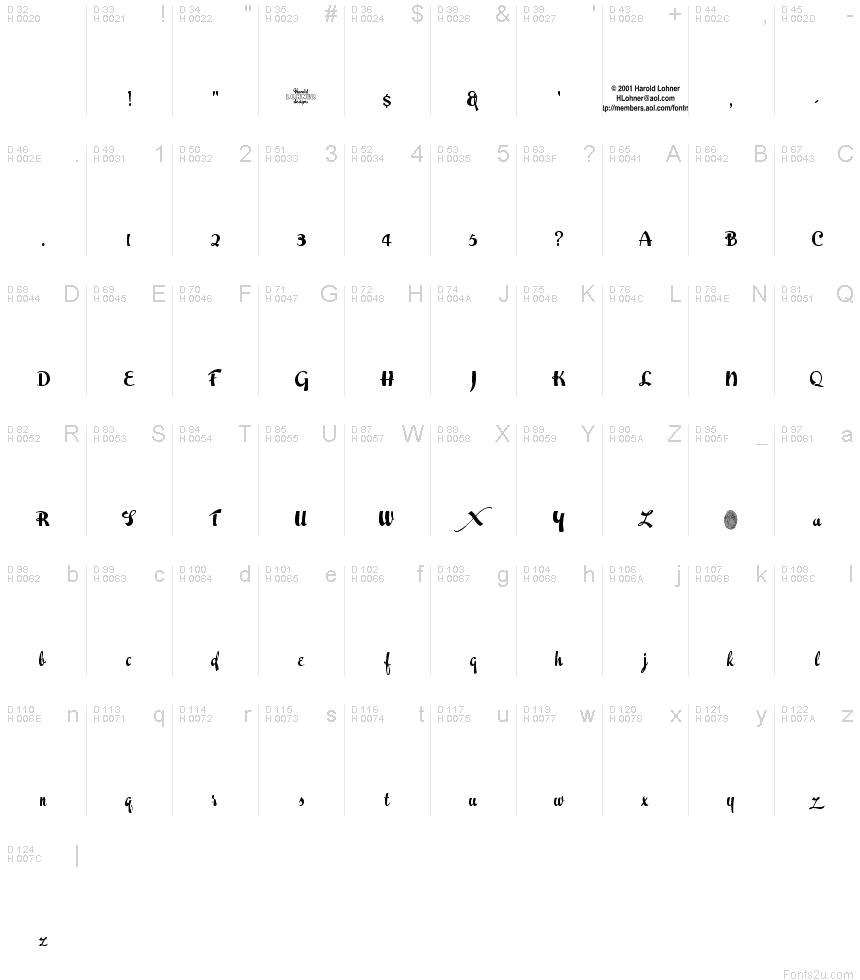
Easter Parade от Harold Lohner — это бесплатный кистевой шрифт с широкими, плавными изгибами и резкими перепадами толщины штрихов. Его прямые знаки отличаются живой пластикой ручной росписи с выразительными петлями и заострёнными соединениями, напоминающими вывески середины XX века.
Его жизнерадостные ностальгические формы отлично подходят для упаковки, особенно сладостей, подарков и сезонных товаров. Та же театральная экспрессия способна оживить афиши мероприятий и графику для индустрии развлечений. В издательском деле шрифт будет уместен на обложках кулинарных книг и в праздничных журнальных материалах, вдохновлённых расписанными вручную вывесками или праздничными иллюстрациями.
Easter Parade